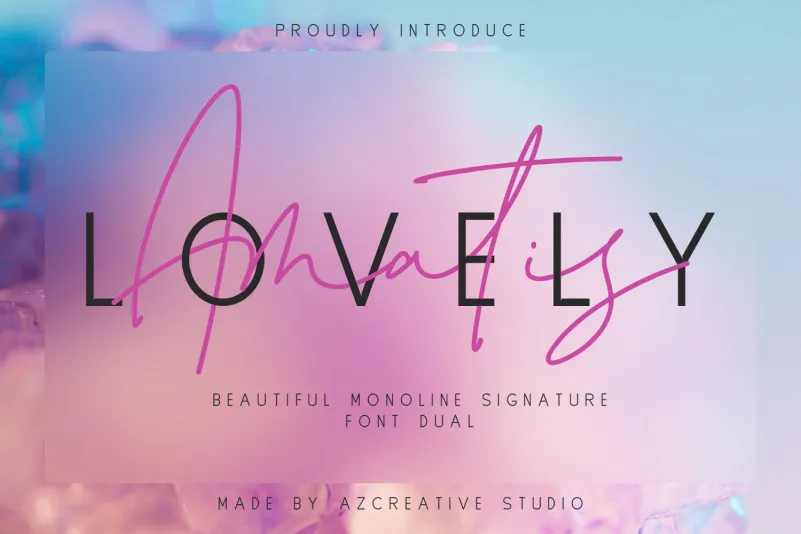
Lovely Amatis Font – Download Grátis
Esta é uma fonte assinatura especial (de escrita manuscrita e sans serif). Ela foi projetada com um cuidado meticuloso que torna esta fonte perfeitamente adequada para marcas de texto única, como nomes de empresas ou logos. A fonte tem o PUA (Unicode Precomposed Unicode Alternative) encodada, uma característica que lhe permite acessar todos os gílios e swashes com facilidade. Lovely Amatis foi cuidadosamente meticulosa e muito detalhada. Esta é uma fonte de escolha perfeita para aqueles buscando algo elegante e único em seu próximo projeto gráfico.